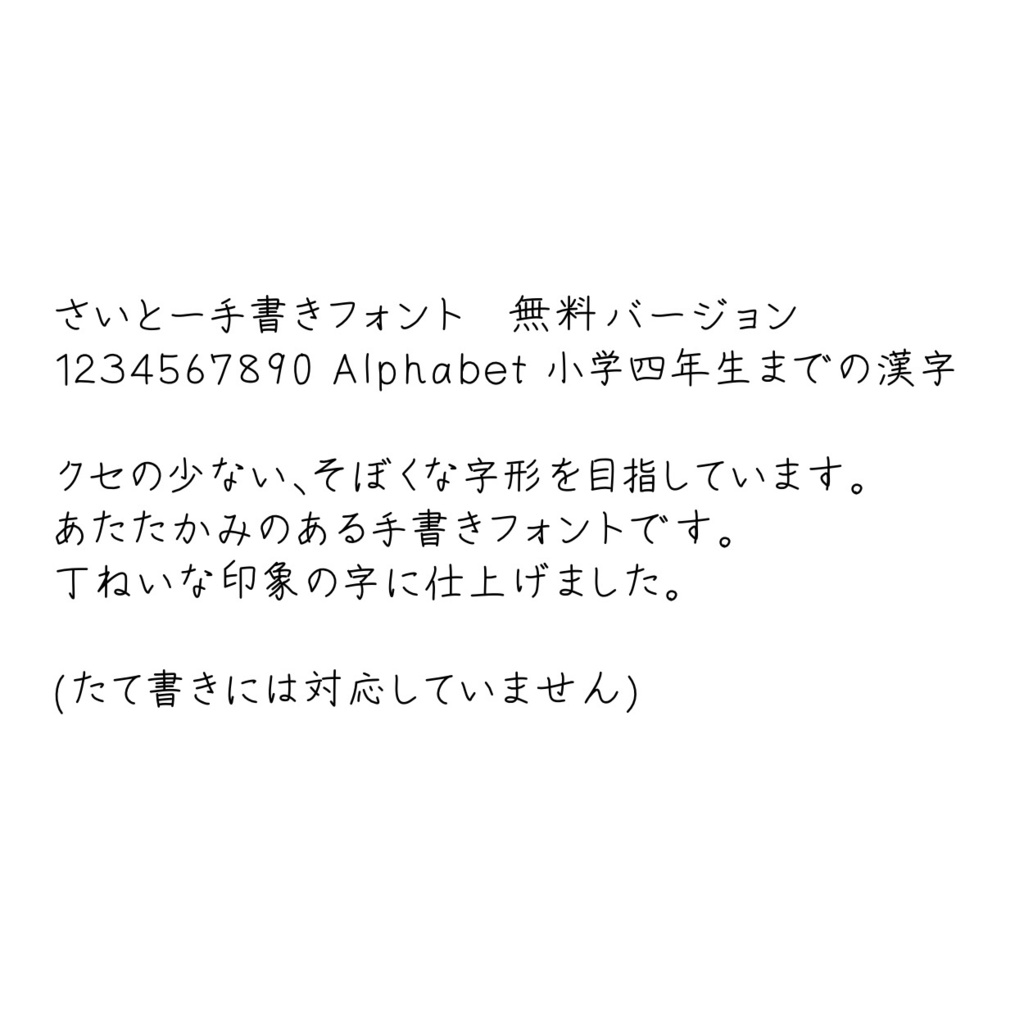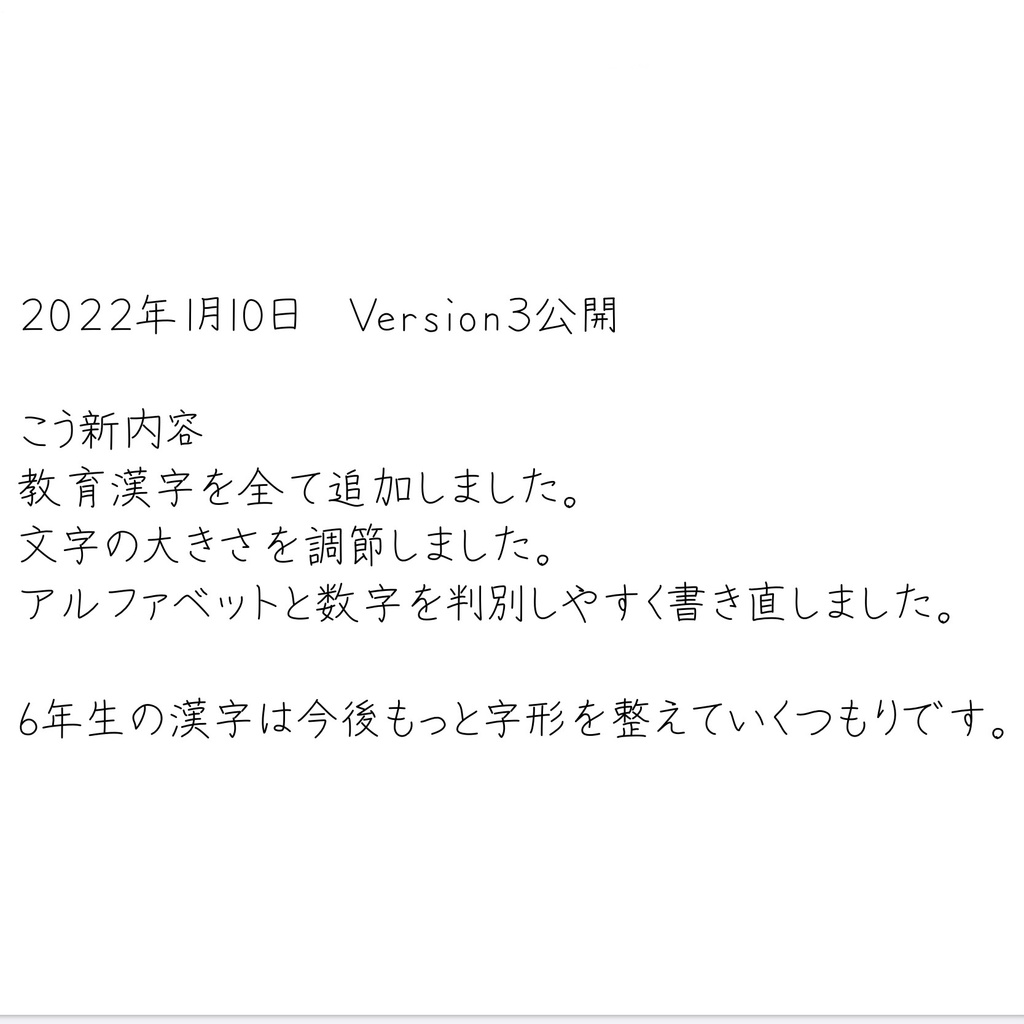
さいとー手書きフォント
画像の通りです。一文字一文字手書きで作成しました。 ファイル名がVer.2になってますがVer.3です 縦書きには対応していません。 ・著作権は放棄していません。著作権は私さいとーに帰属します。 ・フォントファイルの改変や再配布はやめてください。 ・商用にもお使いいただいて構いませんが、このフォントを使って作られた製作物の商標登録はやめてください。 ・このフォントの価値そのものを使用した商品(書写のお手本など)や有料のサービス(書写の講座などで使用するなど)の販売・提供はやめてください。 ・このフォントを使用して発生した問題について、私さいとーは一切責任をとりません。 ☆将来、教育漢字まで網羅した有料版を販売するつもりです。